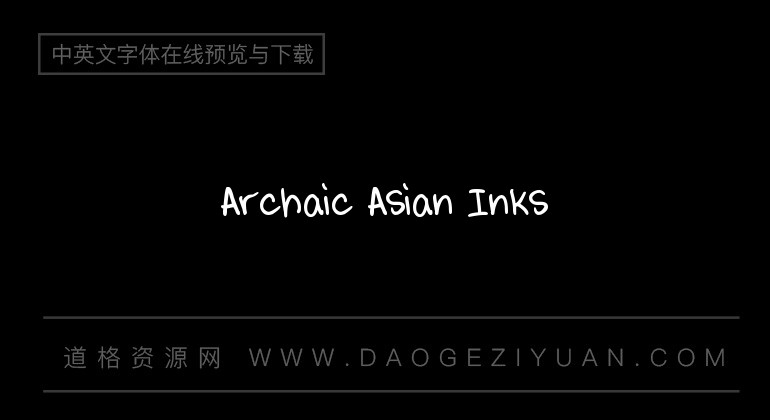
Archaic Asian Inks 字体是一款仿古的东亚风格手写字体,其灵感来源于中国、日本和韩国等地传统书法和绘画艺术。这款字体的特点是线条流畅、笔画有力、结构简洁,整体呈现出一种古朴、雅致的美感。 Archaic Asian Inks 字体包含三种不同的风格:中国的隶书、日本的行书和韩国的楷书。每种风格的字体都有不同的笔画粗细和曲线设计,以适应不同的排版需求。 此外,Archaic Asian Inks 字体还包括许多特殊符号和标点符号,如箭头、星星、月亮等,可以用于设计和排版中,为作品增添一些特别的元素。 总之,Archaic Asian Inks 字体是一款非常适合用于文学、艺术和设计领域的字体,可以为作品增添一些古朴、优雅的气息。内容介绍
Archaic Asian Inks是一款非常不错的手写艺术字体,具有很好的视觉感,适合于文化类的宣传设计、商业类品牌的广告和产品包装设计以及个性化文字排版等较多场景。